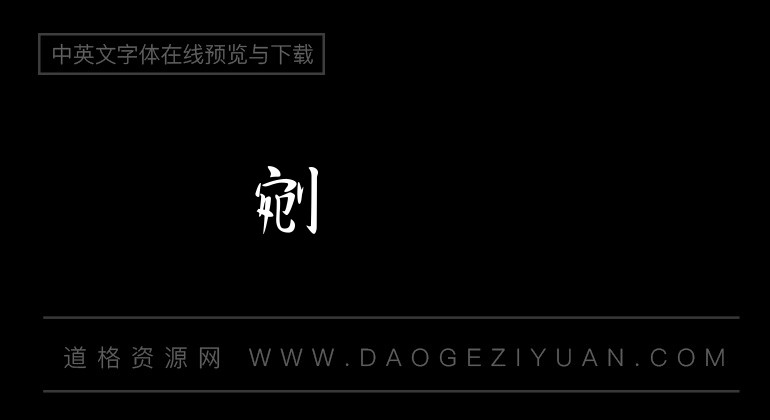
华康行书体
? 华康行书体是一种行书字体,它的特点是字形细腻,笔画流畅,字体宽度适中,有较强的表现力,能体现出细腻的曲线感,较为舒服。因此,它常被用于书法、图章、报刊、书籍、书信等排版中,使文字更加美观。
华康行书体是一款非常不错的手写艺术字体,具有很好的视觉感,适合于文化类的宣传设计、商业类品牌的广告和产品包装设计以及个性化文字排版等较多场景。